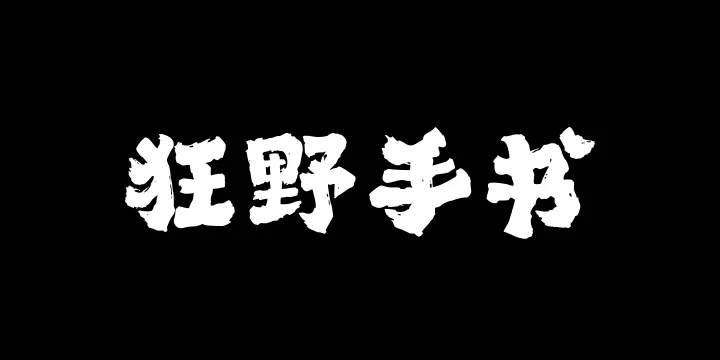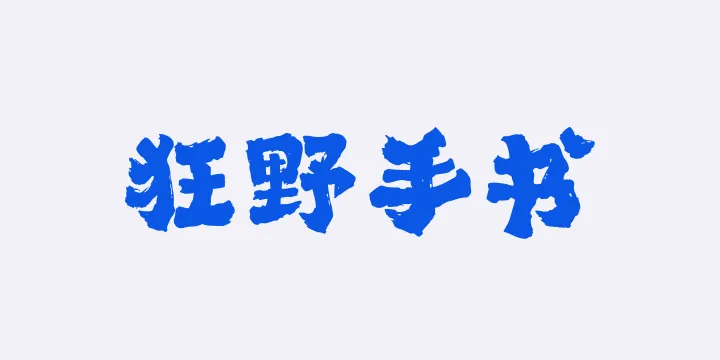
山海狂野手书W By 山海字库 商用字体
字体全名: 山海狂野手书W
字体简介: 山海狂野手书,是一款全新的毛笔风字体,包含汉字9169个,符号200+个。该字体的毛笔笔锋狂野有力,非常醒目!字形古朴浑厚,在浑厚的同时而又极富张力,桀骜不驯的特性,霸气外露。它的笔画充满力量感,组合搭配极富强烈的节奏感。在粗细的纵横间,拥有非常规的张力特性。笔画的飞白效果使字体的气息更加流畅,笔画间的关系密不可分,同时也增加了字体的自由洒脱之感。